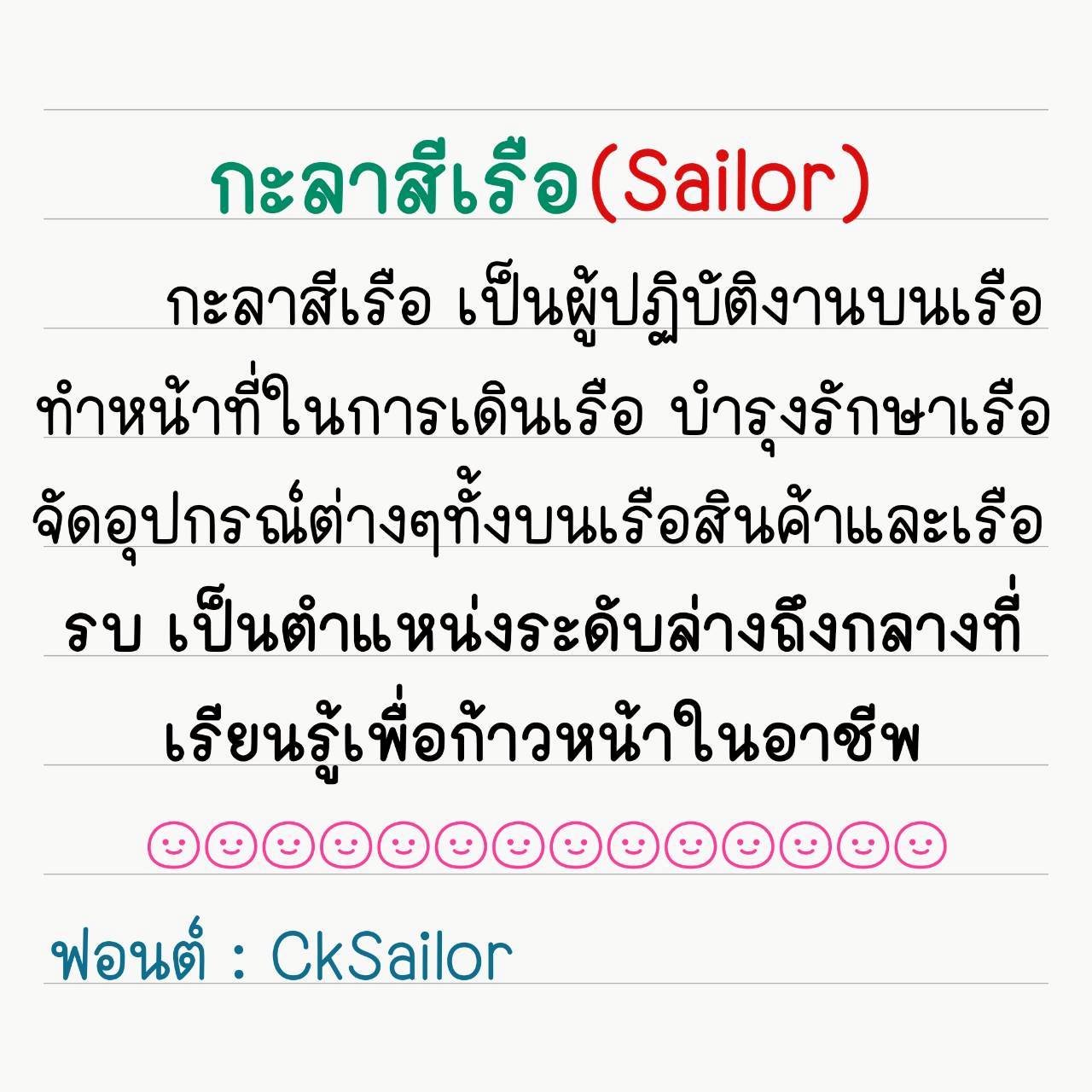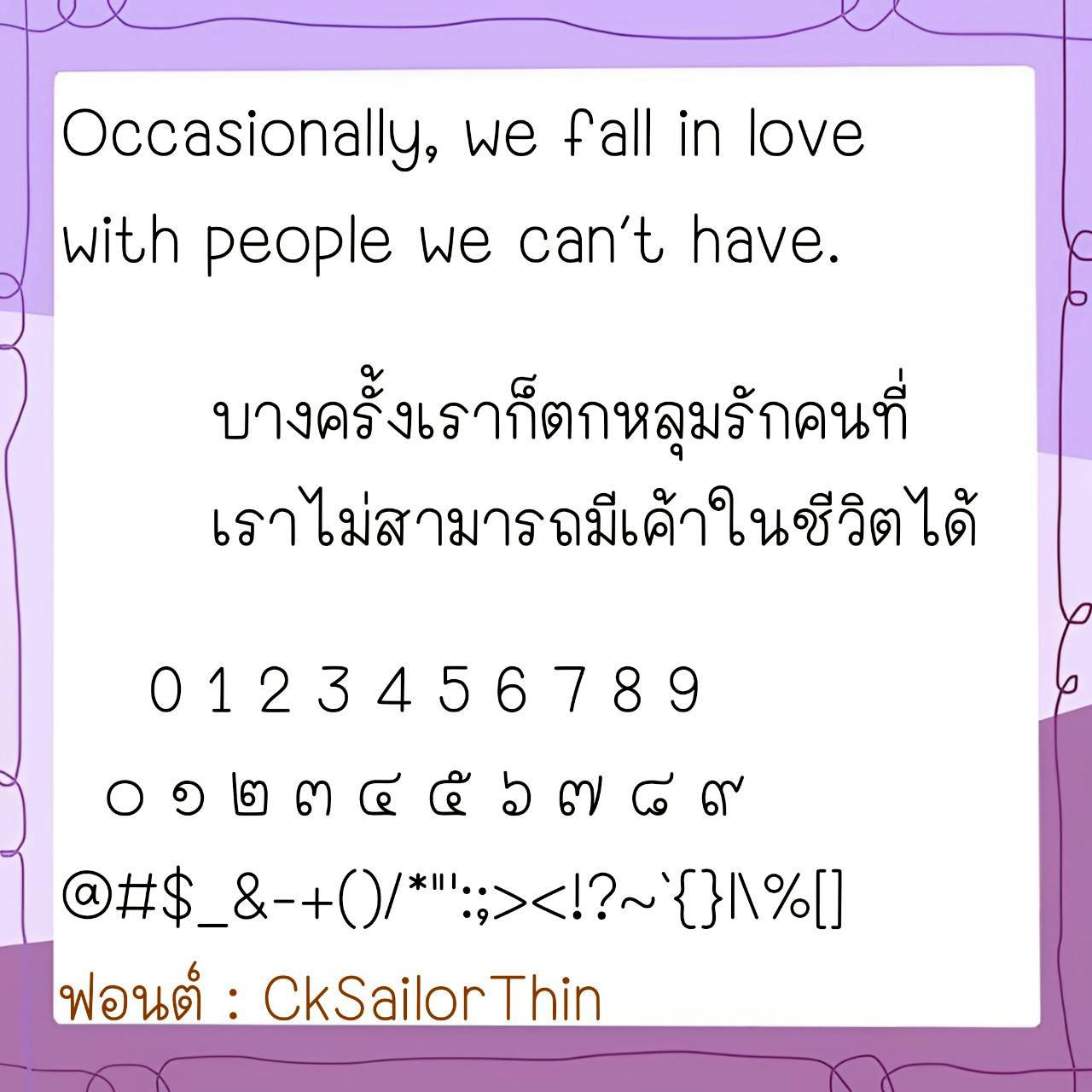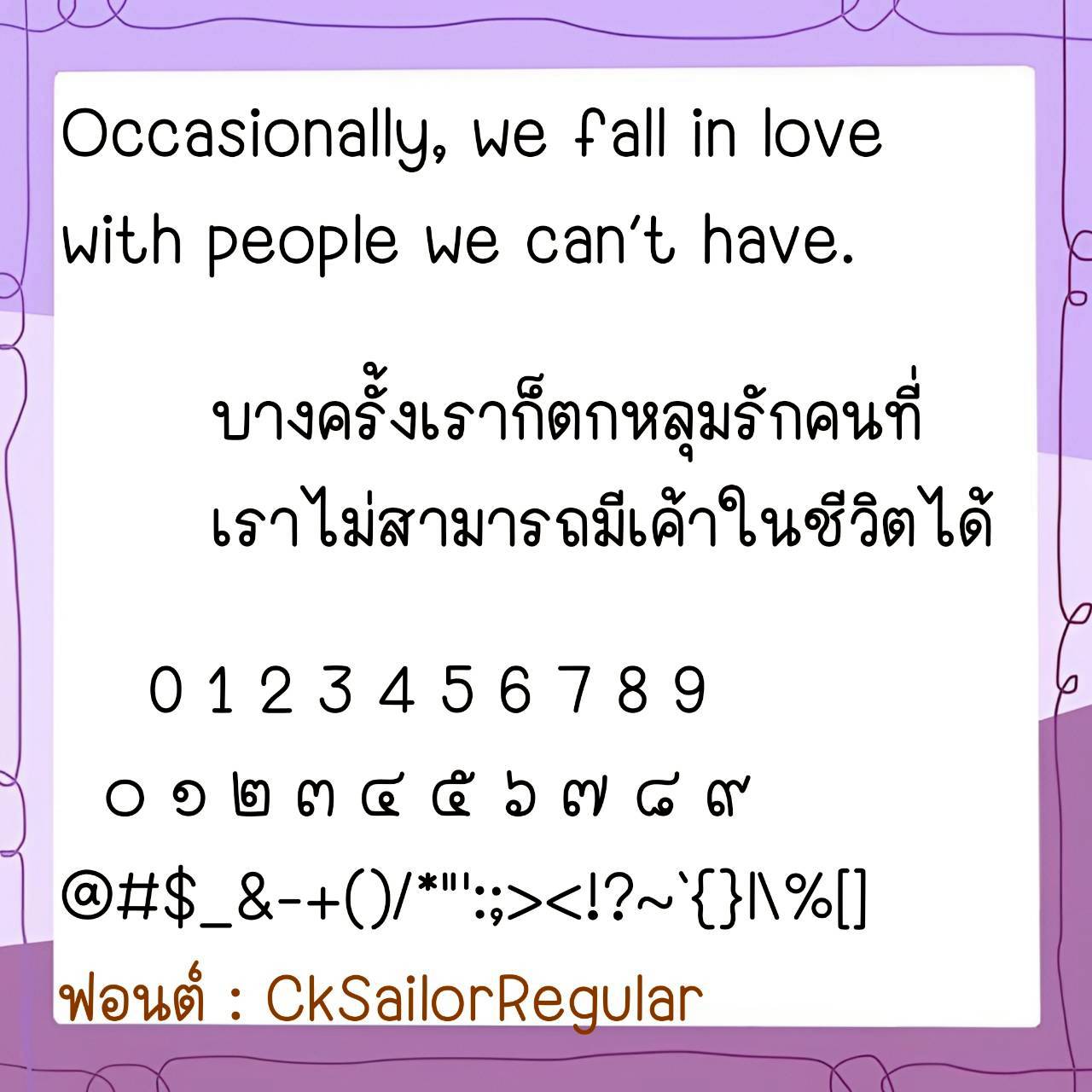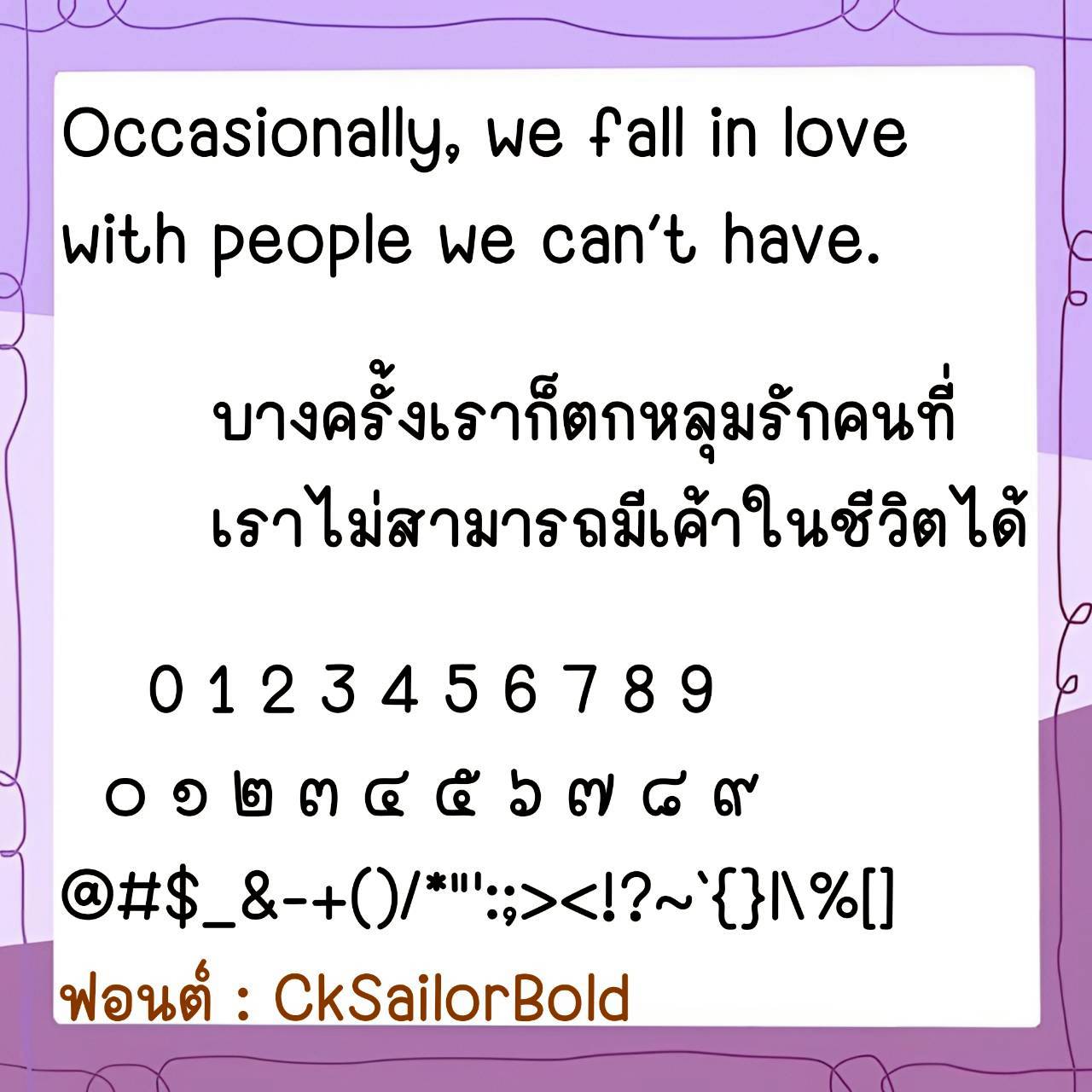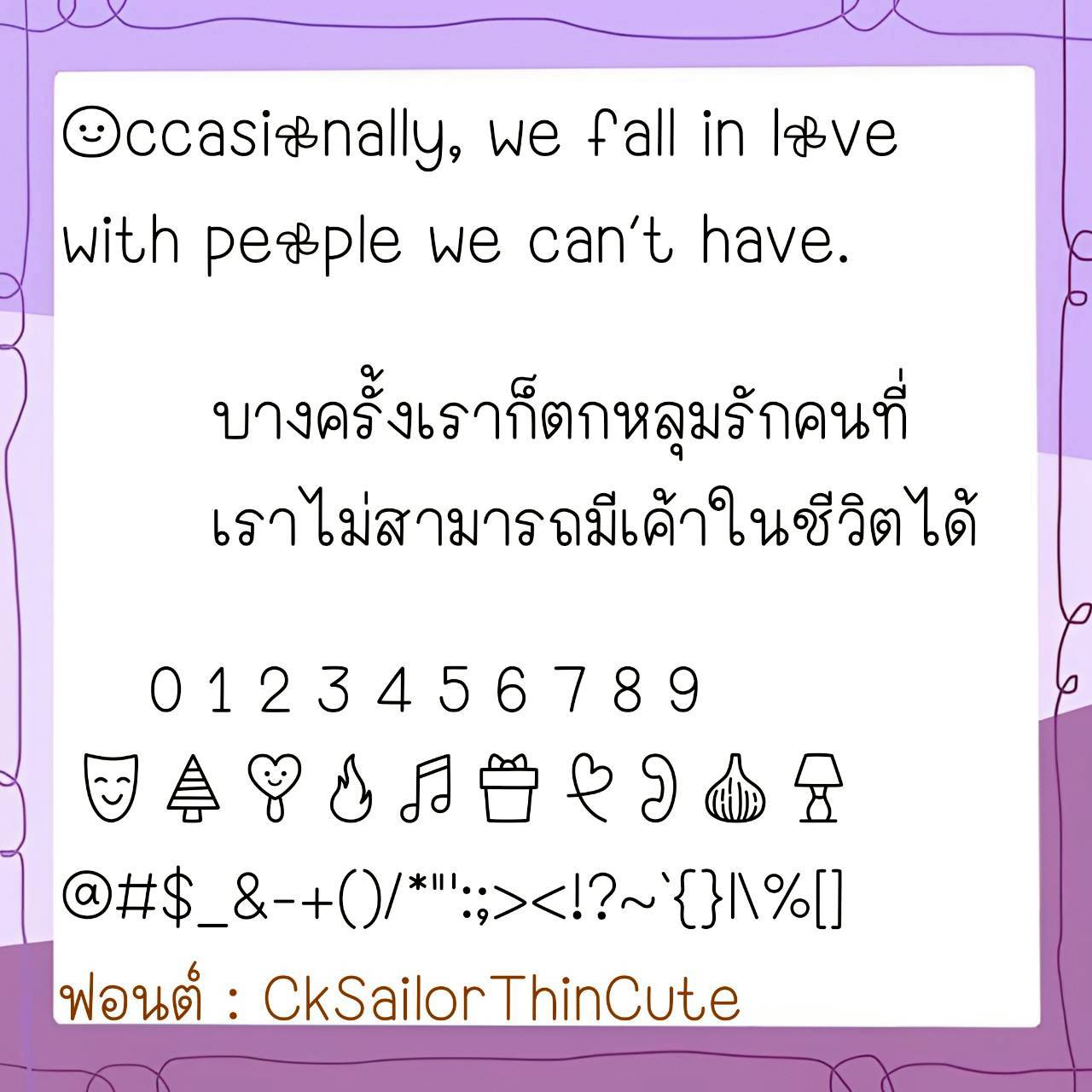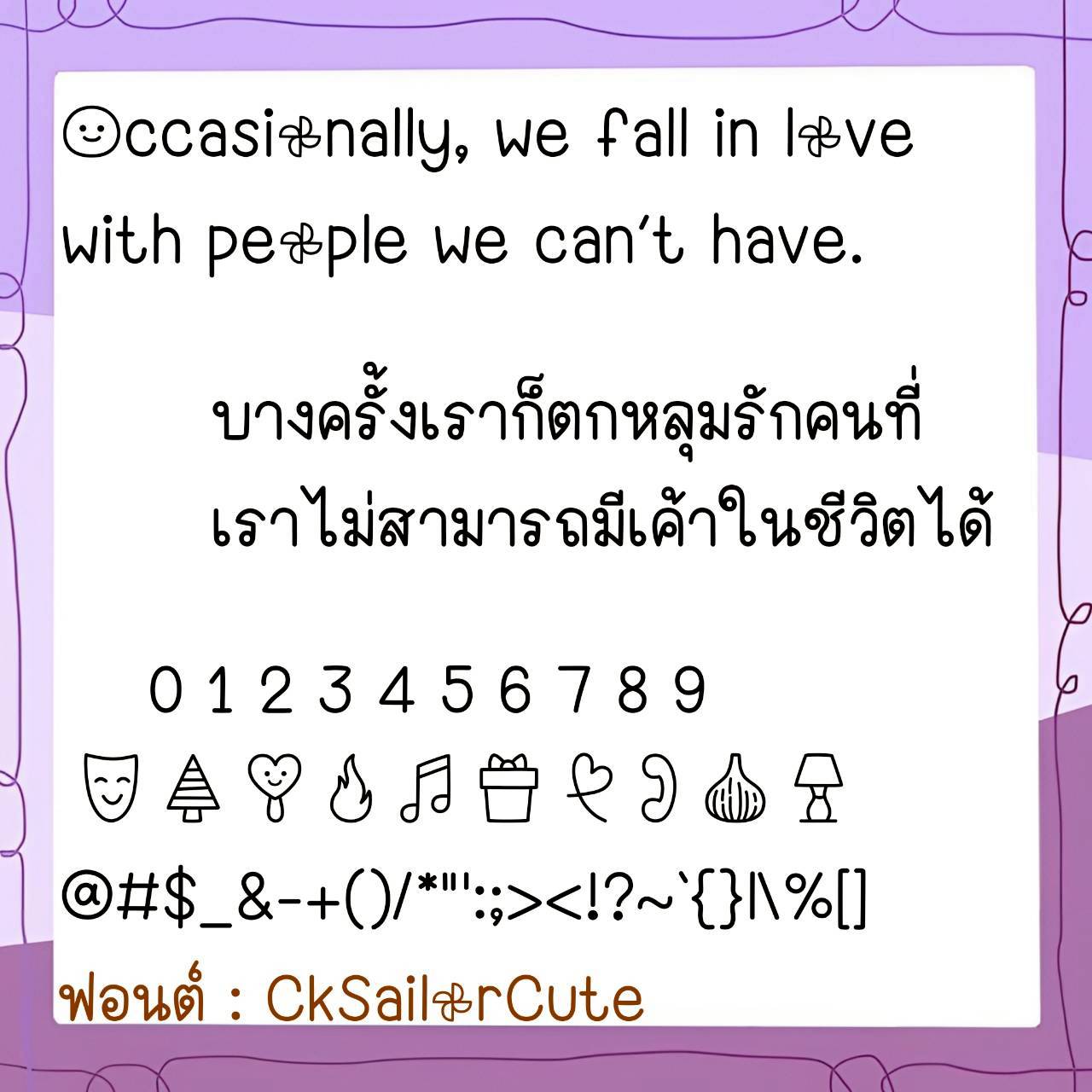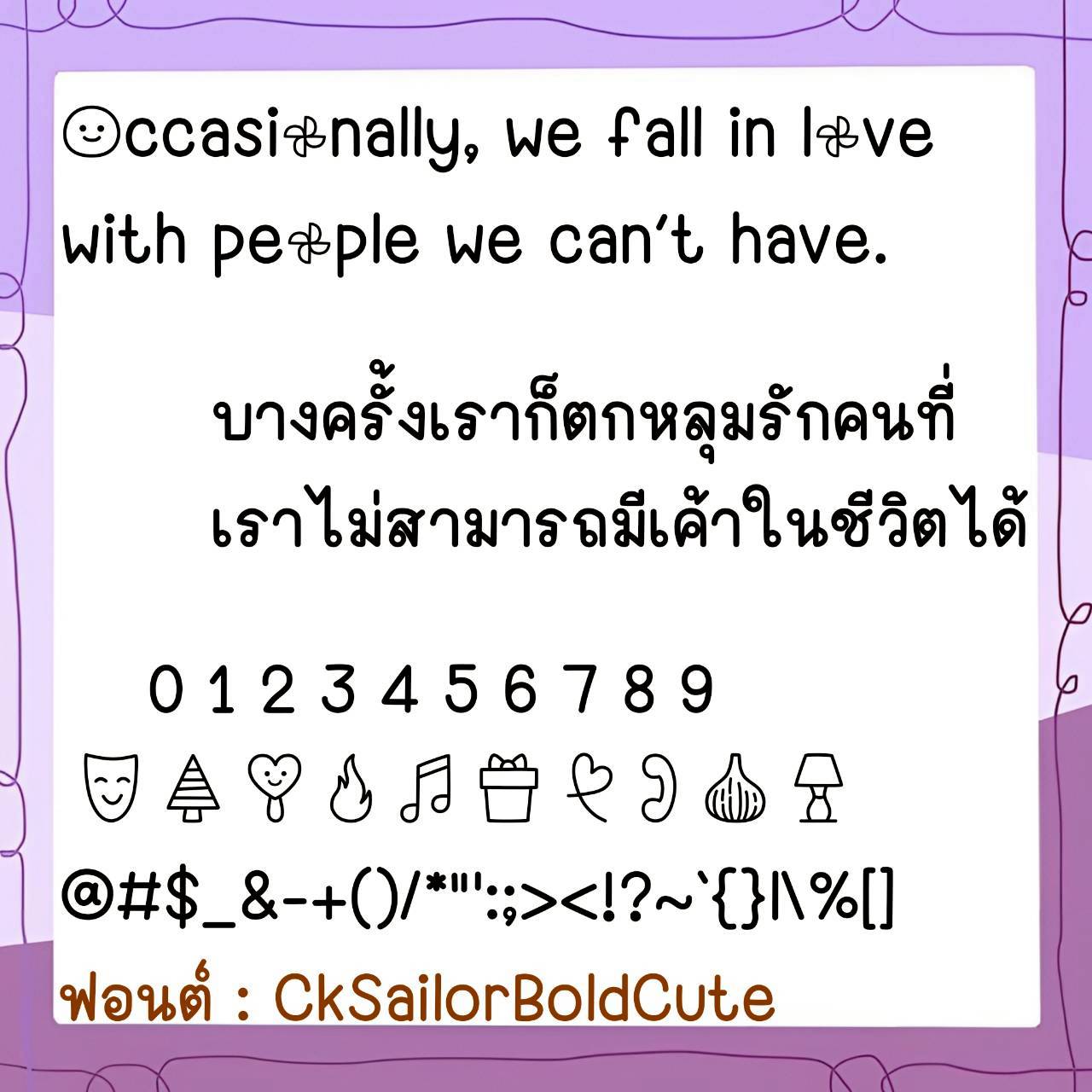
Font CkSailor
🔸 ฟอนต์ลายมือแนวเรียบร้อย ตัวกึ่งเหลี่ยมดูดีแบบไทยๆ เน้นความเป็นระเบียบ อ่านง่ายสยายตา และยังมีไฟล์อิโมจิน่ารักๆที่ใช้แทนเลขไทยให้ด้วยค่ะ 🥰💙
🔹 A neat, handwritten font with semi-square characters that has a stylish Thai look. It emphasizes order, is easy to read, and is pleasing to the eye. There are also cute emoji files that can be used to replace Thai numerals. 🥰💙